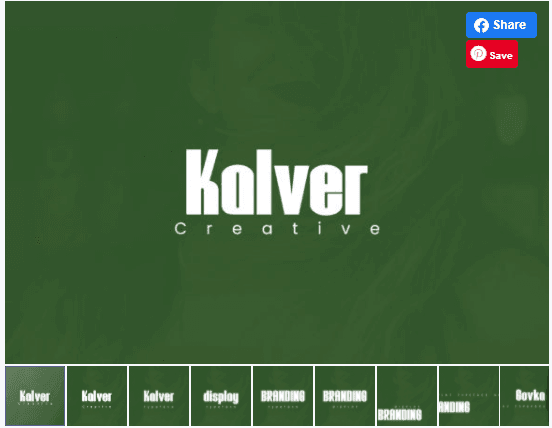
Kalver Font
Kalver - это стильный, минималистичный и современный дисплейный шрифт. Этот шрифт идеально подходит для написания веб-дизайнов, визиток и всего остального, что требует уникального подхода.